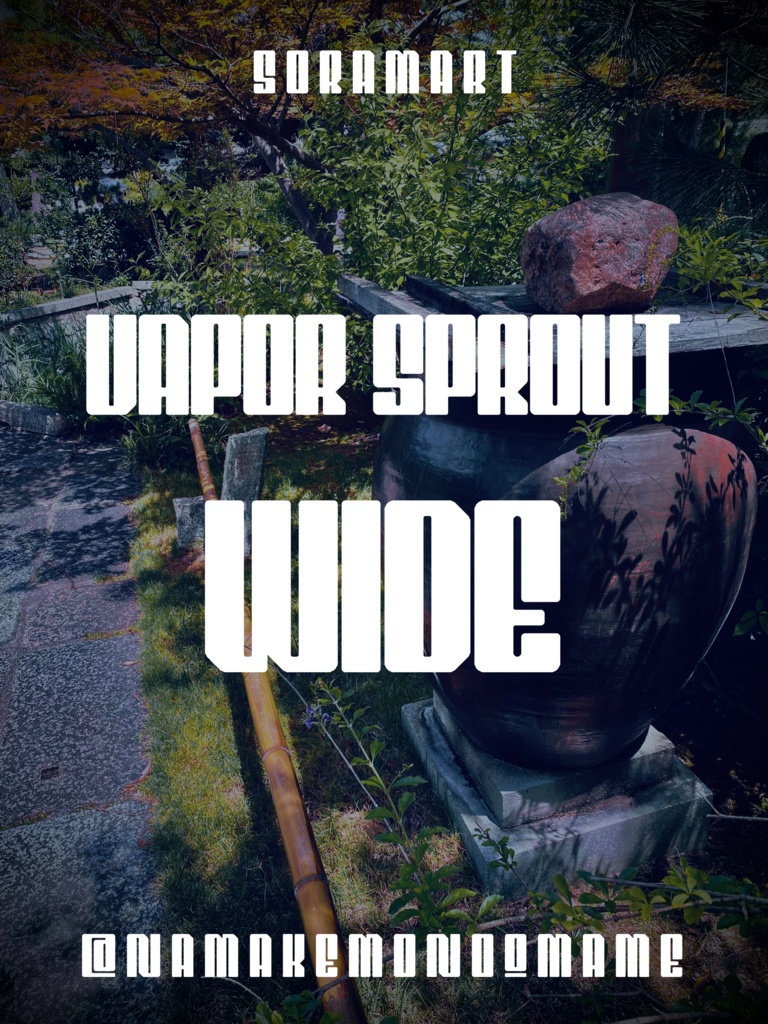
そらマートフォントデータ”Vapor Sprout Wide”ダウンロード商品¥ 2,500カートに入れるギフトとして贈る「ギフトとして贈る」とはレトロモダン調の超縦長フォントを太字化した "Vapor Sprout Wide" です。 「TrueTypeフォントファイル」という形式です。 ダウンロードした後、Zipファイル内のデータをインストールしてお使いください。 このフォントは商用利用可となっております。 お客様の制作・創作活動のお役に立てれば幸いです。 ※使用上の注意事項などは、添付のReadmeをお読みください。そらマートFANBOX開設中フォント・書体フォントデータ”Solid Voltage Strike”そらマート¥ 200フォント・書体フォントデータ”Solid Voltage”そらマート¥ 0フォント・書体フォントデータ”Henge Edge Rock”そらマート¥ 2,500フォント・書体フォントデータ”Henge Edge Tall”そらマート¥ 0フォント・書体フォントデータ”Henge Edge”そらマート¥ 0フォント・書体フォントデータ”Chisel Stroke Wide”そらマート¥ 2,500フォント・書体フォントデータ”Chisel Stroke”そらマート¥ 2,500フォント・書体フォントデータ”Crushed Can Serif Empty”そらマート¥ 2,500フォント・書体フォントデータ”Crushed Can Serif Wide”そらマート¥ 2,500フォント・書体フォントデータ”Crushed Can Serif”そらマート¥ 2,500フォント・書体フォントデータ”Dolce Cube Tall”そらマート¥ 2,500フォント・書体フォントデータ”Dolce Cube”そらマート¥ 2,500フォント・書体フォントデータ”Eight-bit Quest Wide”そらマート¥ 2,500フォント・書体フォントデータ”Eight-bit Quest”そらマート¥ 2,500フォント・書体フォントデータ”Tonik Crate”そらマート¥ 2,500フォント・書体フォントデータ”Vapor Sprout Edge”そらマート¥ 2,500フォント・書体フォントデータ”Vapor Sprout”そらマート¥ 2,500フォント・書体フォントデータ”Star Shoot Ray”そらマート¥ 2,500フォント・書体フォントデータ”Star Shoot Black Wide”そらマート¥ 2,500フォント・書体フォントデータ”Star Shoot Black”そらマート¥ 2,500もっと見る